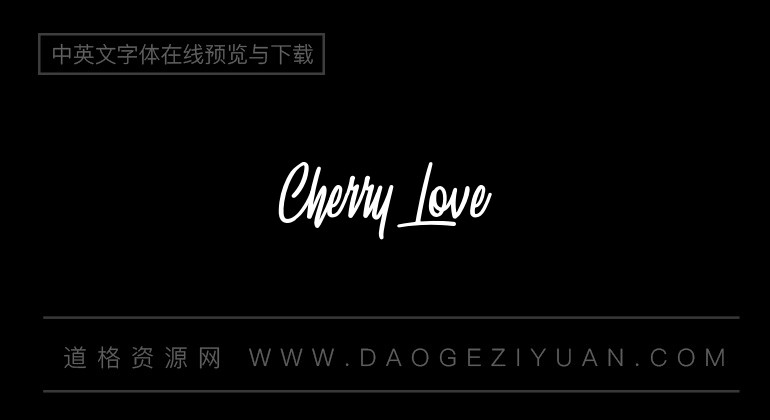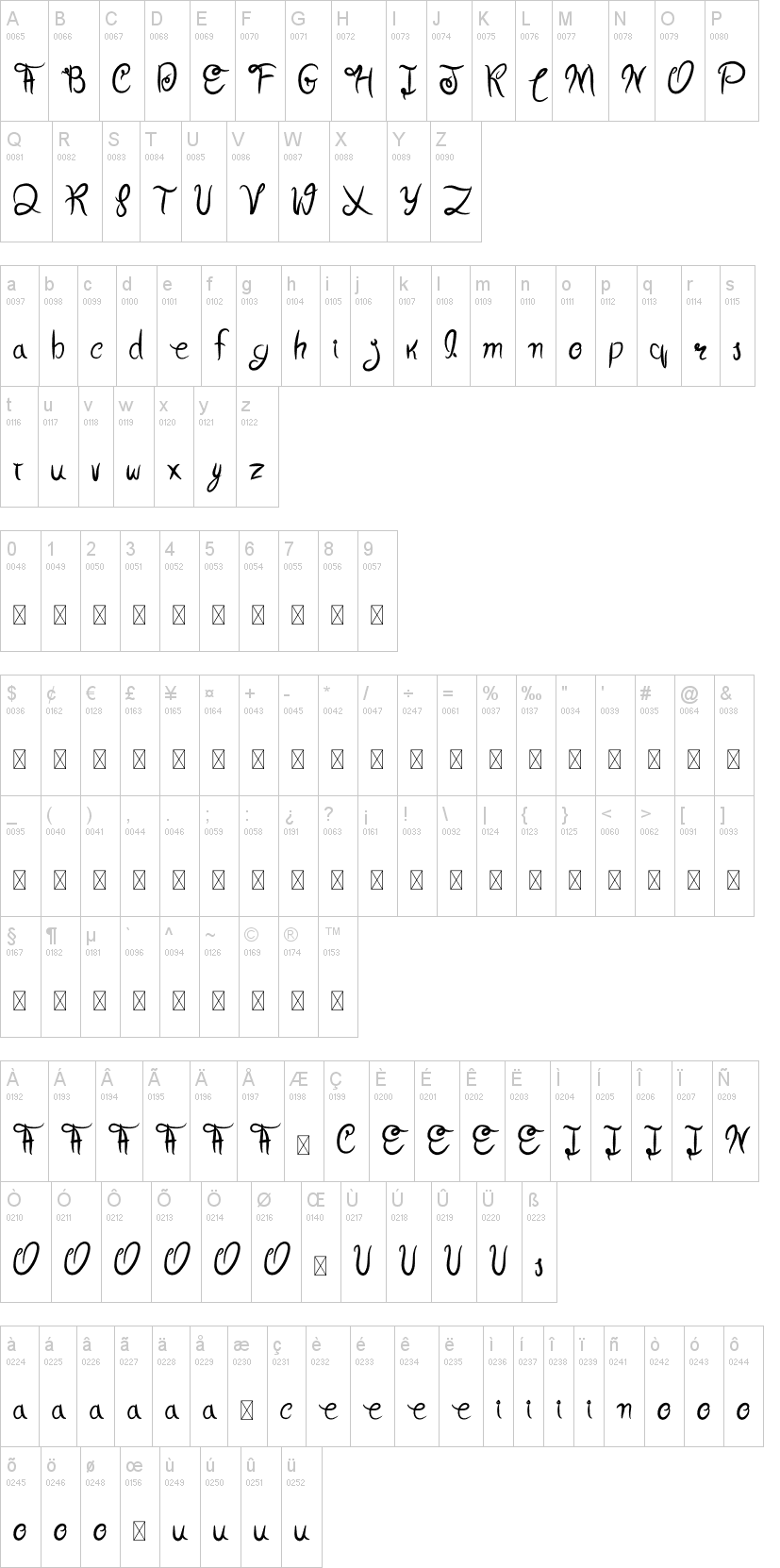
Cherry Love
Cherry Love 是一款卡通字体,由 FontFabric 公司设计,它具有温暖、可爱、活泼的特点。字体的曲线精致,让字体充满了活力,适合用于儿童的文字排版,也可以用于礼品、卡片等多种设计中。Cherry Love 字体拥有大量的细节,两个大写字母之间有细节的连接,让整个字体更加精致。此外,它还有多种符号,可以满足你的各种设计需求。
Cherry Love是一款非常不错的手写艺术字体,具有很好的视觉感,适合于文化类的宣传设计、商业类品牌的广告和产品包装设计以及个性化文字排版等较多场景。